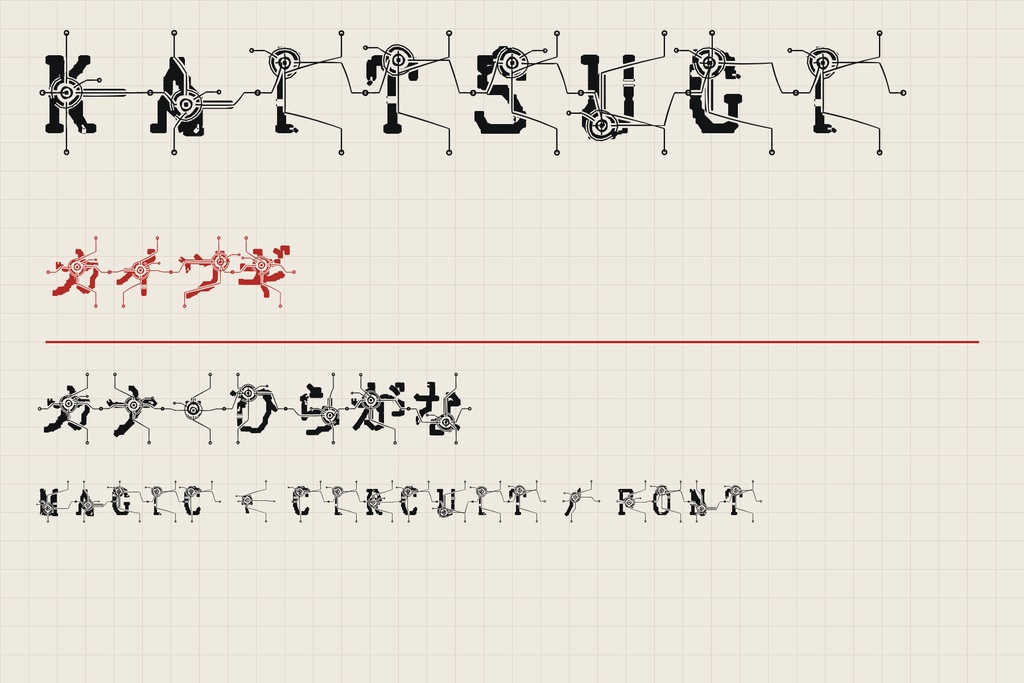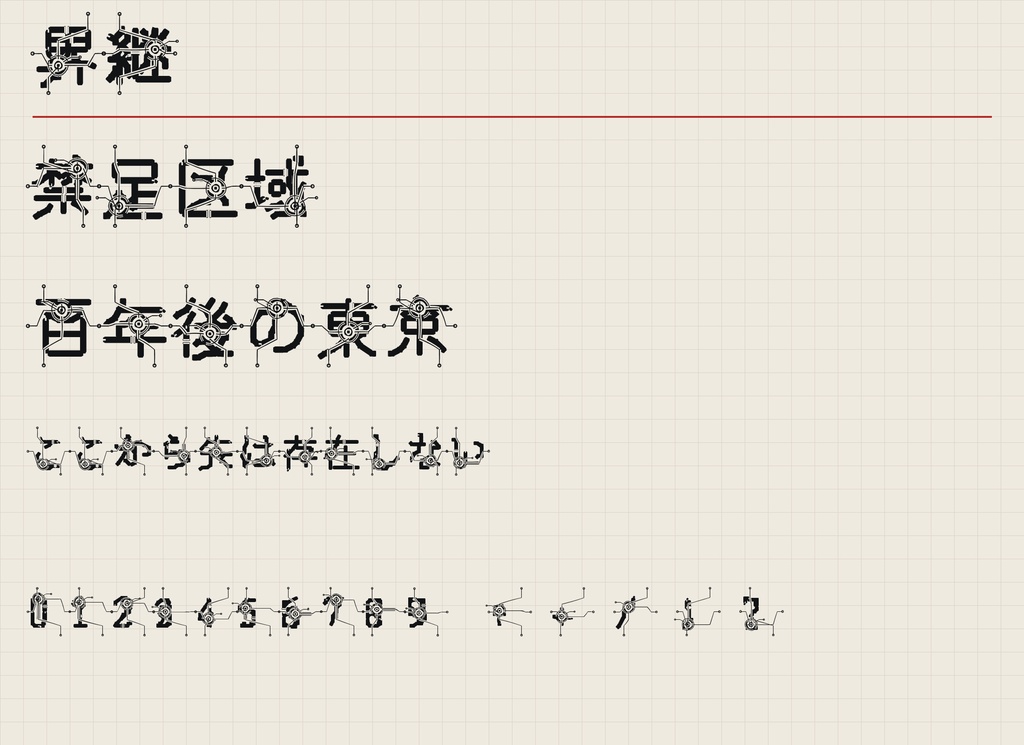
【界継 / KAITSUGI】魔法陣回路・結界風 日本語フォント|英字かな版・常用漢字版
文字の密集部に「コア」が生まれ、周囲の字画を巻き込みながら有機的な回路へ変形する日本語ディスプレイフォントです。 隣り合う文字の接続線が連続し、文章全体が結界・都市回路・魔法陣のような造形になります。 ■ バリエーション ・簡装版(英字・かな・記号) 380円 英数字、ひらがな、カタカナ、基本記号を収録 ・完全版(常用漢字2,136字収録) 980円 簡装版の収録文字に加え、常用漢字2,136字をすべて収録 ■ 形式 TrueType(TTF) / Windows・macOS ■ 利用 個人・商用利用可。ロゴ、動画、ゲーム、印刷、配信、同人・商業作品に使用できます。クレジット不要。 フォントデータの再配布・共有・転売は禁止です。詳細はZIP内の利用規約をご確認ください。 ■ 字形由来 字形骨格にはGlyphWiki KAGEデータを使用し、独自の機械化・密度コア配置・局所ワープ処理を施しています。 ※見出し・タイトル向けの装飾書体です。小サイズの本文用途には向きません。